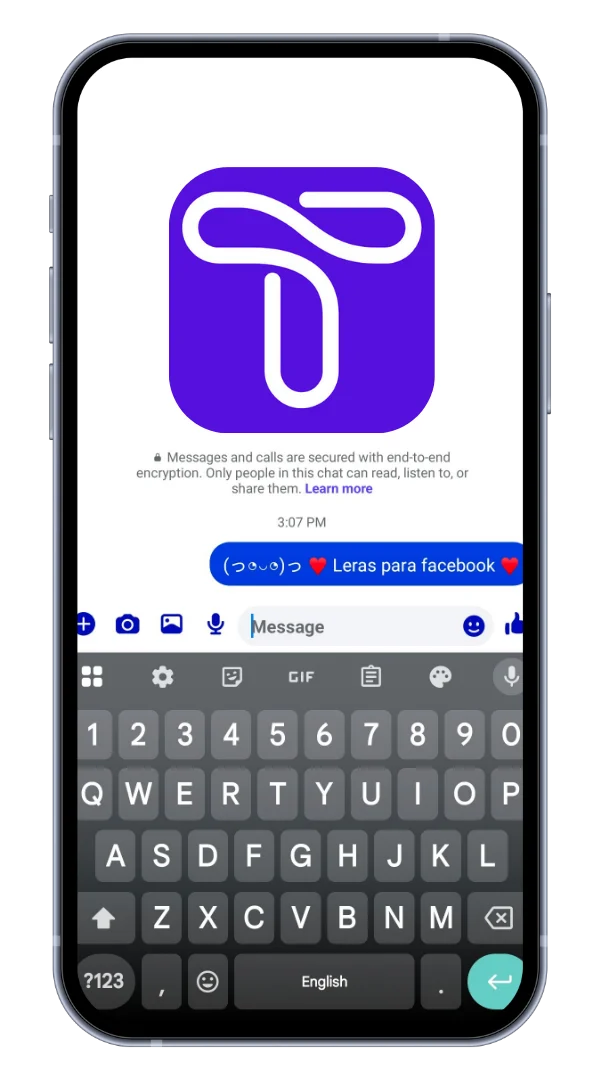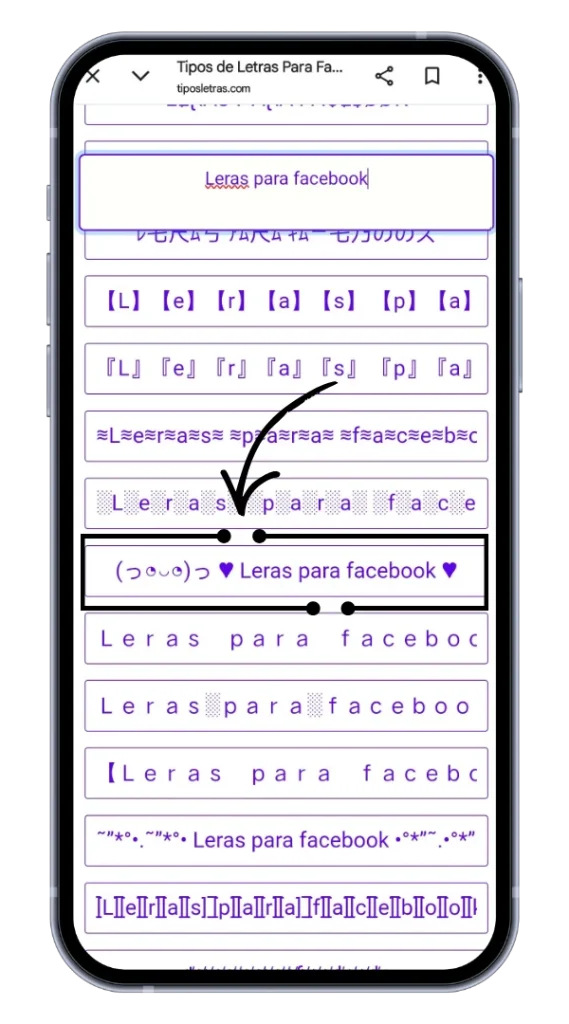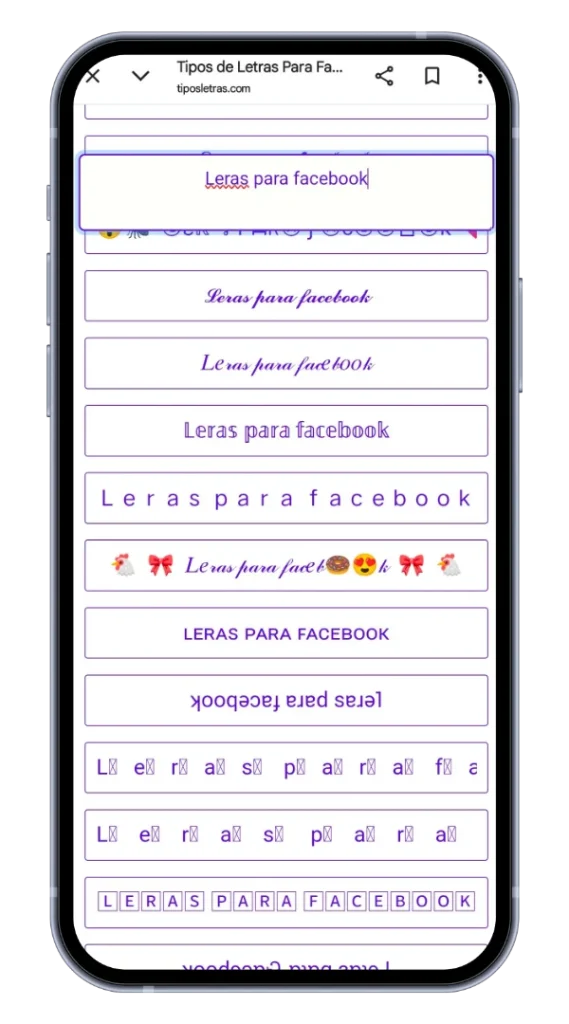
Letras Para Facebook Bonitas Copiar y Pegar
En el mundo digital de hoy, cada detalle de nuestras publicaciones cuenta. Desde las imágenes hasta los textos, todo influye en cómo otros perciben nuestro perfil. Las letras para Facebook se han convertido en una herramienta esencial para destacar en esta red social. Permiten darle un estilo único a tus publicaciones y transmitir tu personalidad de manera creativa. Si quieres explorar más opciones de estilo, puedes visitar nuestra colección de tipos de letras bonitas que te ayudarán a encontrar el estilo perfecto para cada momento.
Letras Para Facebook
¿Qué son los Tipos de Letras para Facebook y por qué usarlas?
Los tipos de letras para Facebook son variaciones de la fuente predeterminada que ofrece la plataforma. Estas fuentes permiten cambiar la apariencia de tus textos en publicaciones, comentarios, nombres de perfil y biografías. No se trata solo de estética; son herramientas que ayudan a captar la atención, expresar emociones y hacer que tu contenido sea más memorable.
Usarlas tiene varias ventajas. Por un lado, diferencian tus publicaciones de las demás en un feed saturado. Por otro, te permiten experimentar con tu estilo personal. Desde letras elegantes hasta fuentes más llamativas o divertidas, estas herramientas convierten un texto común en algo que refleja tu identidad.
Haz que tus Publicaciones Sean Más Atractivas con Tipos de Letras para Facebook
El uso de tipos de letras facebook puede transformar una publicación ordinaria en un contenido llamativo. Por ejemplo, al escribir un mensaje inspirador, aplicar una fuente elegante puede reforzar el impacto del texto. De igual forma, fuentes más divertidas pueden hacer que un mensaje casual resulte más entretenido y memorable.
Además, estas letras son fáciles de copiar y pegar, lo que significa que puedes personalizar tu perfil y tus publicaciones sin complicaciones. Experimentar con distintos estilos te permite descubrir qué tipo de fuente se adapta mejor a tu personalidad y al mensaje que quieres transmitir.
Usos Prácticos de los Tipos de Letras para Facebook
Los tipos de letras para Facebook no solo son estéticos; también tienen aplicaciones prácticas que mejoran la interacción y la presentación de tu contenido. A continuación, exploramos algunos de los usos más comunes.
Personalización del Nombre de Perfil
Cambiar la fuente de tu nombre de perfil es una forma efectiva de destacar. Una letra elegante o divertida puede atraer miradas y generar curiosidad entre tus amigos o nuevos contactos. Personalizar tu nombre no altera tu identidad, pero sí permite expresar tu estilo único dentro de la plataforma.
Diseñar Publicaciones Atractivas
El contenido visual no se limita a imágenes o videos. Las publicaciones de texto también pueden ser atractivas si se combinan con tipos de letras facebook. Usar fuentes distintas para destacar frases clave o mensajes importantes puede aumentar la visibilidad de tus publicaciones y fomentar la interacción de tu audiencia.
Crear Biografías Creativas
La biografía de Facebook es tu carta de presentación. Aplicar diferentes estilos de letras puede darle vida y personalidad a esta sección. Desde letras bonitas hasta cursivas o negritas, cada estilo permite que tus palabras comuniquen más allá de su significado literal. Una biografía creativa refleja quién eres y capta la atención de quienes visitan tu perfil.
Características de los Tipos de Letras para Facebook Disponibles
Existen múltiples estilos de letras facebook que puedes utilizar para personalizar tu contenido. Entre las características más destacadas se encuentran:
• Negritas y cursivas: ideales para resaltar palabras clave o frases importantes.
• Versalitas: letras que combinan mayúsculas con tamaño reducido, dando un toque sofisticado.
• Góticas y decorativas: perfectas para mensajes artísticos o temáticos.
• Letras raras y divertidas: para añadir creatividad y originalidad a tus publicaciones.
• Subrayadas o tachadas: útiles para enfatizar o jugar con la tipografía.
Estos estilos permiten experimentar con distintos formatos y adaptarlos según el contexto de cada publicación.
Beneficios de Usar Letras Personalizadas en Facebook
Utilizar letras para Facebook ofrece beneficios que van más allá de la estética:
• Mayor visibilidad: publicaciones únicas llaman más la atención en el feed.
• Expresión personal: reflejan tu estilo y personalidad.
• Interacción mejorada: textos llamativos aumentan los comentarios, likes y compartidos.
• Diferenciación: ayudan a destacar frente a perfiles comunes.
• Versatilidad: se pueden usar en nombres, biografías, publicaciones y comentarios.
Explorar distintos tipos de letras facebook es una forma divertida y efectiva de reflejar tu personalidad y mejorar la interacción en la plataforma. Con creatividad y consistencia, tus textos no solo comunicarán palabras, sino también estilo y carácter, logrando un perfil único y memorable para todos tus amigos y seguidores.